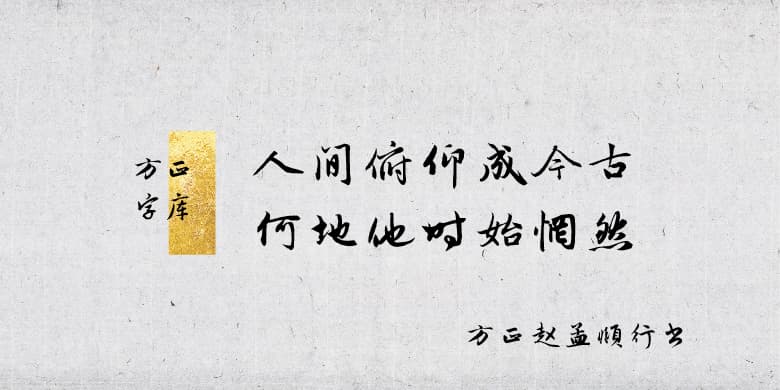
品牌:方正字库中华精品字库设计师:郭毓海发行时间:2020字库编码:简繁扩展(GBK)分类:常规书写·毛笔字体属性:精品字
·字形特征
以赵孟頫的书法作品《前后赤壁赋》《洛神赋》及其他信札作为主要开发依据,字形流美华丽,外似柔润而内实坚强,形体端秀而骨架劲挺,每个字都铿锵有力。行书大气、笔法圆熟、形意结合。
·关于赵孟頫
赵孟頫(1254-1322年)元书画家。字子昂,号雪松道人,湖州(今属浙江)人。本为宋宗室,降于元朝,累官至翰林学士承旨。工于书法,尤精正、行书和小楷,所写碑版甚多,圆转遒丽,人称“赵体”。亦善画山水、人物、墨竹和花鸟,皆以笔墨圆润苍秀见长。着有《松雪斋集》,卒赠魏国公,谥文敏。
设计师:郭毓海